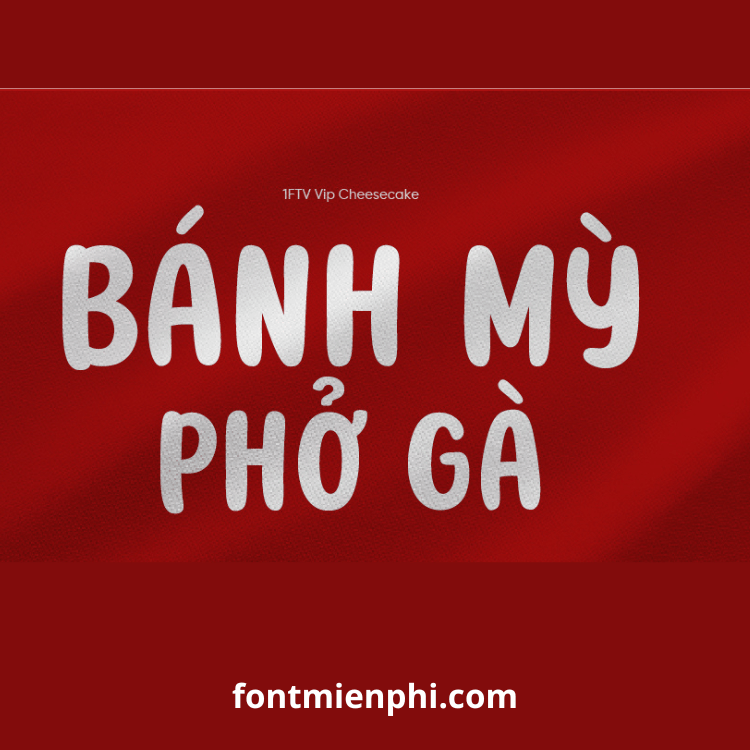
Font Việt hóa 1FTV Vip Cheesecake
Mô Tả Chi Tiết Font Việt Hóa “1FTV VIP Cheesecake”
1. Giới Thiệu
1FTV VIP Cheesecake là font chữ handwriting (viết tay) cao cấp với nét chữ mềm mại, thanh lịch, mang phong cách sang trọng và nữ tính. Font được thiết kế tinh tế với các nét uốn lượn nhẹ nhàng, phù hợp cho các dự án thiết kế thời trang cao cấp, mỹ phẩm, nhà hàng, thiệp mời, và branding cần sự tinh tế.
2. Đặc Điểm Nổi Bật
✔ Phong cách chữ viết tay sang trọng: Nét chữ thanh mảnh, uốn cong tinh tế, tạo cảm giác quý phái.
✔ Hỗ trợ đầy đủ Tiếng Việt: Bao gồm đầy đủ dấu và ký tự Unicode, tương thích với mọi phần mềm thiết kế (Photoshop, Illustrator, CorelDRAW, Canva…).
✔ Đa dạng ký tự: Hỗ trợ chữ hoa, chữ thường, số, và các ký tự đặc biệt cơ bản.
✔ Dễ đọc, dễ ứng dụng: Phù hợp cho cả tiêu đề và đoạn văn ngắn trong thiết kế.
3. Ứng Dụng Phổ Biến
- Thiết kế thời trang cao cấp, túi xách, phụ kiện.
- Nhận diện thương hiệu mỹ phẩm, spa, làm đẹp.
- Thiệp cưới, thiệp mời sang trọng.
- Menu nhà hàng, quán café cao cấp.
- Content sang trọng trên mạng xã hội.
Tip: Kết hợp font với tone màu trung tính (beige, trắng ngà, vàng nhạt) sẽ tăng độ sang trọng cho thiết kế!